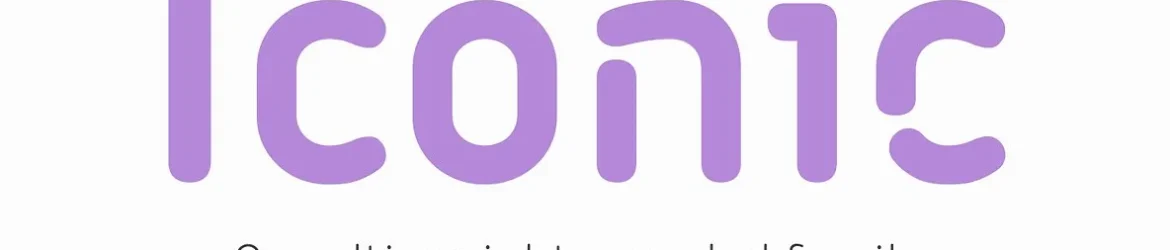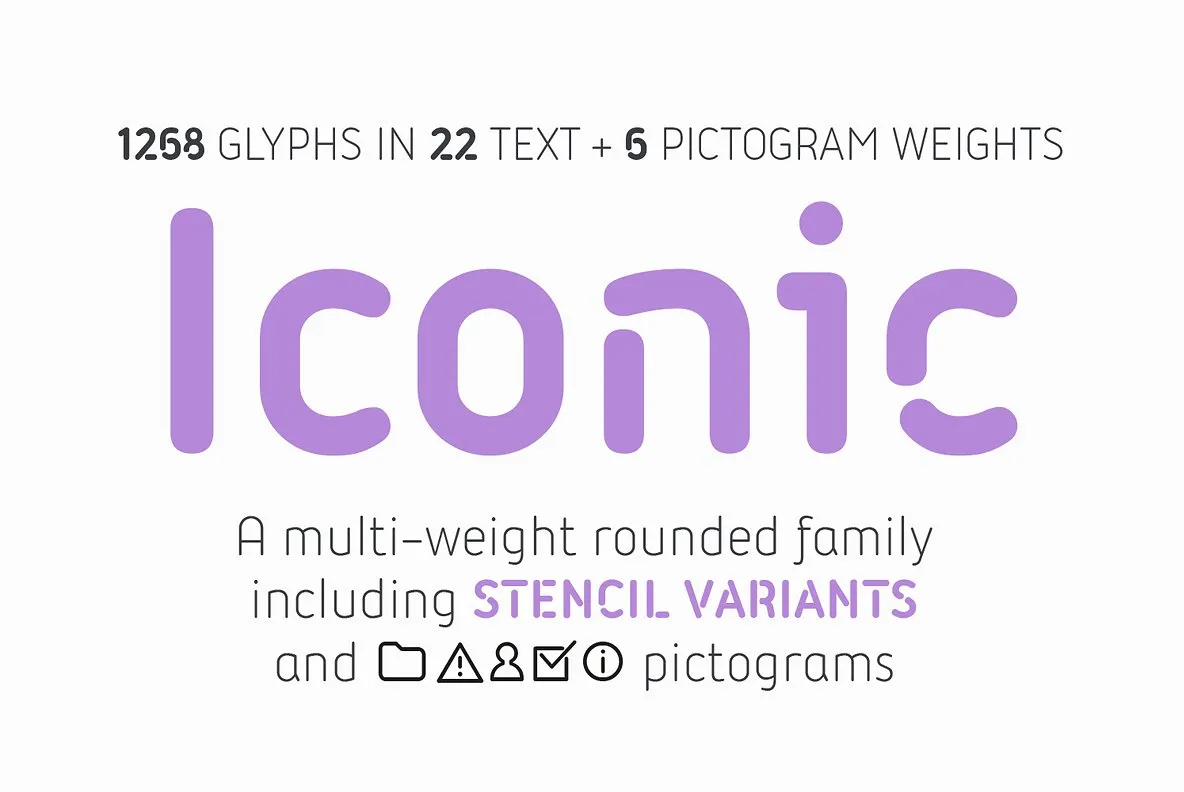
A nova família de fontes sans-serif Iconic é uma introdução ao design moderno para uso em diversas aplicações digitais. Desenvolvida pelo designer Andrea Tartarelli, junto com Cosimo Lorenzo Pancini e Francesco Canovaro, a fonte foi criada pela Zetafonts sob o conceito de minimalismo técnico e contemporâneo. Iconic é uma família multimeios projetada para um uso eficiente em editoriais, interfaces e design de informação, adaptando-se com facilidade ao espaço disponível. Com suas formas suaves e redondas baseadas em geométrica circular, a fonte incorpora sutis toques humanistas que tornam o estilo mais informal e leitor. A família Iconic oferece uma extensa gama de pesos para uso tanto em texto quanto no display. Em configurações de corpo de texto, a fonte excede com clareza de leve até bold, proporcionando opções média e regular para ajustes finos ao formato do texto; enquanto na utilização de aplicações visuais, ela permite expressões infinitas desde o peso fino mais fino até o super-seguro. Esta família também inclui uma subfamília stencil com design técnico agressivo para complementar as formas básicas e regulares da família. Perfecto para uso em identidade visual e design de interação, a seis pesos da fonte stencil pode ser usada junto à família principal para um enriquecimento estético do texto.